Von Simple Sans bis zum psychedelischen Futurismus
Die variable Schrift Fonts hat sich von einem Trend zu einem echten typografischen Grundnahrungsmittel entwickelt. Schriftzüge mit einem Twist, amerikanisches Retro und eine neue Welle von Fonts , die den Traditionalismus ablehnt, sind ebenfalls Teil der aktuellen Entwicklung im Schriftbereich.
Um den Puls der typografischen Trends zu fühlen, haben wir uns an Ryan Crouchman gewandt, Partner, Vizepräsident und Executive Creative Director bei LG2 - Kanadas größter unabhängiger Kreativagentur.
Ryan war auch Jurymitglied beim 13. jährlichen Typografiewettbewerb der Zeitschrift Communication Arts. Er ist jemand, der sich mit Schrift auskennt.
Beständige Trends und etwas Neues
Die erste Frage, die wir Ryan stellten, lautete: Hat er als Jurymitglied des Communication Arts Typography Competition typografische Designtrends gesehen, die MyFonts -Kunden beachten sollten - oder neue typografische Klischees, die sie vermeiden sollten?
Er antwortete, dass es einige eindeutige Trends gab, die sich durch den gesamten Wettbewerb zogen. "Die üblichen Verdächtigen wie Schweizer Revivals, experimentelle Drehbücher und Anspielungen auf das alte Amerika", erklärte Ryan, "die alle sehr schön sein können, wenn sie gut gemacht sind." Er wählte auch etwas Neues aus. Eine Richtung, die ich in letzter Zeit häufig gesehen habe, ist der psychedelische Futurismus". Das ist eine Stil , die den organischen Geist des Jugendstils mit der Experimentierfreudigkeit der Hippiekultur der 1970er Jahre verbindet. Viele gewellte, gewellte Buchstabenformen, oft manipuliert oder von Hand gezeichnet, werden auf sehr ausdrucksstarke Weise verwendet."
Avenir®. Nächste, Helvetica® Now, Neue Haas Unica™, und Univers® Nächste gelten alle als Schweizer Revivals.
Wenn Sie auf der Suche nach experimentellen Drehbüchern sind, MyFonts Schriften wie A Morris Line, Soda Script™., und Bechamel™ könnten die richtige Wahl sein. Die meisten erfolgreichen experimentellen Schriften sind Beispiele für Handlettering.
BrughlerBirthmont, und Dustland sind eindeutige Anspielungen auf die altmodische Americana. Während, Blowing Vesicle, Visualism, und HWT Arabesque™ sind neue Designs, die eindeutig eine Hommage an die Hippiekultur der 1970er Jahre darstellen.
Einfaches, aber wirkungsvolles Rebranding
Ryan fügte schnell hinzu, dass manchmal eine sehr einfache, traditionelle Schrift die richtige Wahl ist. "Wir haben kürzlich KN Crowder umbenannt", erklärt er. "Es handelt sich um ein etabliertes Familienunternehmen, das seit über 70 Jahren hochwertige Türbeschläge entwickelt und herstellt. Die aktualisierte Marke sollte Innenarchitekten und Designer direkt ansprechen und die klare, zeitlose und gut verarbeitete Natur ihrer Produkte widerspiegeln.
"Um dies zu erfassen, haben wir AG Book® (ein Berthold-Design, erhältlich unter MyFonts) als primäres Schrift. Die stromlinienförmige Geometrie dieses speziellen Schrift eignet sich gut für kleine Formate, um die Produkte des Unternehmens zu kennzeichnen. Es bietet auch eine unglaubliche Wirkung, wenn es groß auf die Verpackungen gedruckt wird, so dass die Produkte von KN Crowder in Fabrikhallen und auf Baustellen gut sichtbar sind."
Wenn Sie eine klare, zeitlose Schrift Familie in Betracht ziehen, die groß genug ist, um die Anforderungen praktisch aller Branding-Projekte zu erfüllen, sollten Sie vielleicht auch Schrift Designs wie Klassische Groteske™., ein Design aus dem frühen 20. Jahrhundert, das für die heutige digitale Bildbearbeitung neu gestaltet wurde, oder Trade Gothic® Next, eine Sans aus der Mitte des Jahrhunderts, die für die heutigen Anforderungen an das Branding neu gezeichnet wurde.
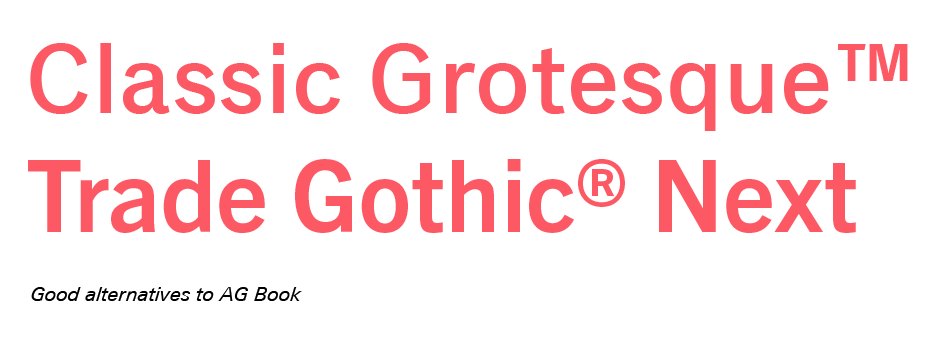
Wir haben Ryan auch gefragt, was ihn bei seinen persönlichen Entscheidungen für Fonts und typografisches Design antreibt. Er sagte uns, dass er jedes Projekt als Gelegenheit sieht, einen neuen typografischen Ansatz zu erforschen, aber er hat auch drei wichtige Faktoren, die seine Methodik bestimmen. "Die Wahl der Schriftart hängt von der Markenpersönlichkeit, den Kommunikationsbedürfnissen und der Zielgruppe ab", sagt er. Wie bei allen Designdisziplinen geht es auch bei Über darum, Form und Funktion auf eine gut durchdachte und interessante Weise miteinander zu verbinden. Manchmal erfordert ein Projekt eine einfache, strapazierfähige Schrift und nicht viel mehr. In anderen Fällen ist etwas Ausdrucksstärkeres erforderlich, um einen einzigartigen Standpunkt zu vermitteln. Es kommt immer darauf an, was sich richtig anfühlt und gut aussieht.
Variable Fonts kann die perfekte Wahl sein
Ryan erzählte uns, dass er und sein Team kürzlich eine Aktualisierung der der visuellen Identität von LG2 - und dass dazu die Entwicklung einer einzigartigen variablen Schrift gehört. "Die variable Fonts gibt uns die Möglichkeit, auf einfache Weise Anwenden Bewegung in unsere Identität einzubauen", erklärte er. "Die von dem kanadischen Typografen und Designer Julien Hébert entworfene Schrift heißt 'Angus', zu Ehren des Viertels, in dem sich unser neuer Hauptsitz in Montreal befindet." Angus ist ein unaufdringliches, aber raffiniertes Design, das auf Kanadas starkes modernistisches Designerbe verweist - und das mit einer einzigen Font Datei.
Auf die Frage, was seiner Meinung nach die aktuellen Typentrends beeinflusst, antwortete Ryan: "Es sind zu viele kulturelle Kräfte im Spiel, um eine umfassende Antwort zu geben. Man kann jedoch mit Sicherheit sagen, dass der technologische Fortschritt die Trends immer auf sehr direkte Weise beeinflusst hat. Ein Beispiel dafür ist die stetige Zunahme von datengesteuerten, generativen und dynamischen typografischen Ausdrucksformen, vor allem im Bereich Kunst und Kultur. Variable Fonts sind auf dem Vormarsch